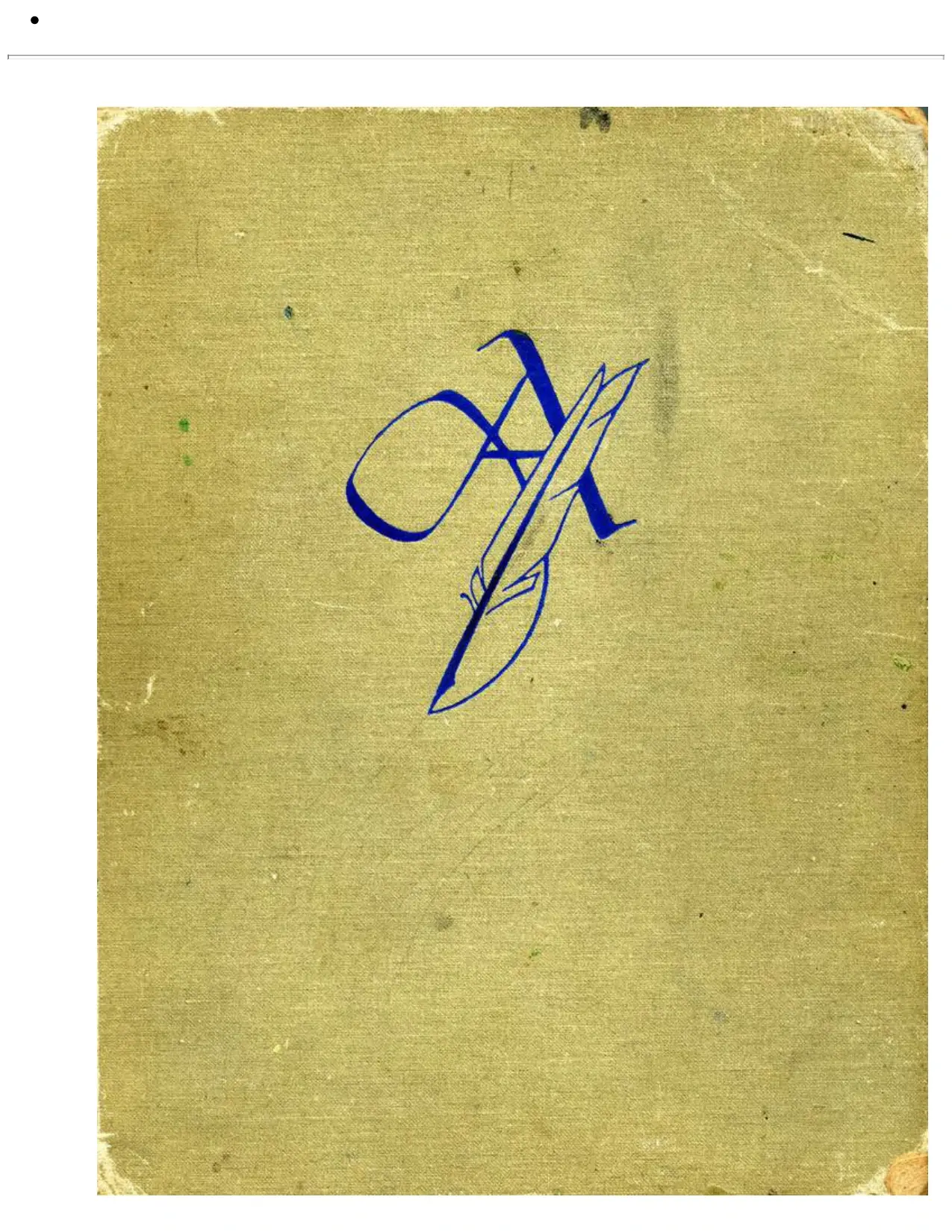
Villu Toots 300 Burtu Veidi – 300 Шрифтов
Grāmata ir latviešu valodā un ietver arī dažādus krievu burtu rakstu piemērus. Tā piemērota lasītājiem, kurus interesē kaligrāfija, tipogrāfija, grafiskais dizains un burtu zīmēšana.
Grāmatas apskats
Villu Toots izdevumā apkopoti mūsdienu rokraksta burtu paraugi, vēsturiskie raksti, ar roku rakstīti burti un iespiedumam paredzēti burtu veidi. Daudzus burtu rakstus ir izveidojis pats autors.
Izdevums skaidro rakstības attīstību no zīmējuma un bilžu raksta līdz alfabēta burtiem. Tajā aplūkoti ēģiptiešu hieroglifi, grieķu un romiešu burti, unciali, pusunciali, karolingu minuskulis, gotiskie raksti, antīkva, ēģiptiešu raksts un groteskie burti.
Grāmatas mērķauditorija ir pašmācības ceļā apgūstošie, zīmēšanas skolotāji, vidusskolu un tehnikumu audzēkņi, mākslinieki, grafiķi, dekoratīvās un lietišķās mākslas pārstāvji, reklāmas un poligrāfijas nozares darbinieki.
Ko atradīsiet grāmatā
- Mūsdienu rokraksta burtu paraugus.
- Vēsturiskos rakstus un to attīstības skaidrojumu.
- Ar roku rakstītus un iespiedumam paredzētus burtus.
- Latīņu alfabēta burtu formas un dažādu stilu piemērus.
- Krievu burtu rakstu paraugus.
- Praktiskus burtu izpildījuma piemērus.
- Norādījumus izcilāko burtu stilu konstruēšanai.
Kāpēc šī grāmata ir nozīmīga
Izdevums parāda rakstības formas kā kultūras vēstures daļu un sasaista burtu attīstību ar dažādiem vēstures periodiem. Tas vienuviet apvieno vēsturisku pārskatu, burtu paraugus un praktisku ievirzi.
Grāmata var būt noderīga tipogrāfijas, kaligrāfijas, grafikas un burtu zīmēšanas apguvē. Tās materiāls īpaši orientēts uz latīņu alfabēta lietotājiem, vienlaikus iekļaujot arī krievu raksta piemērus.